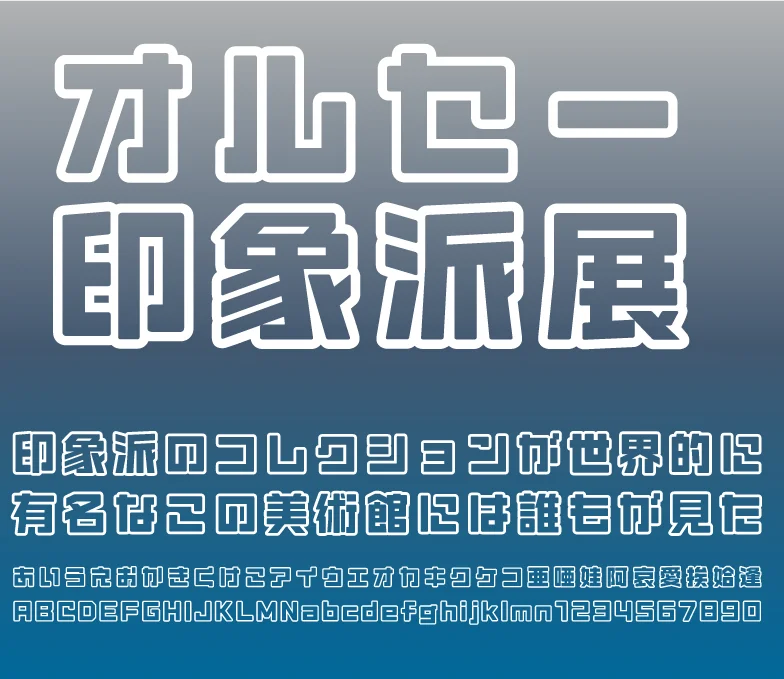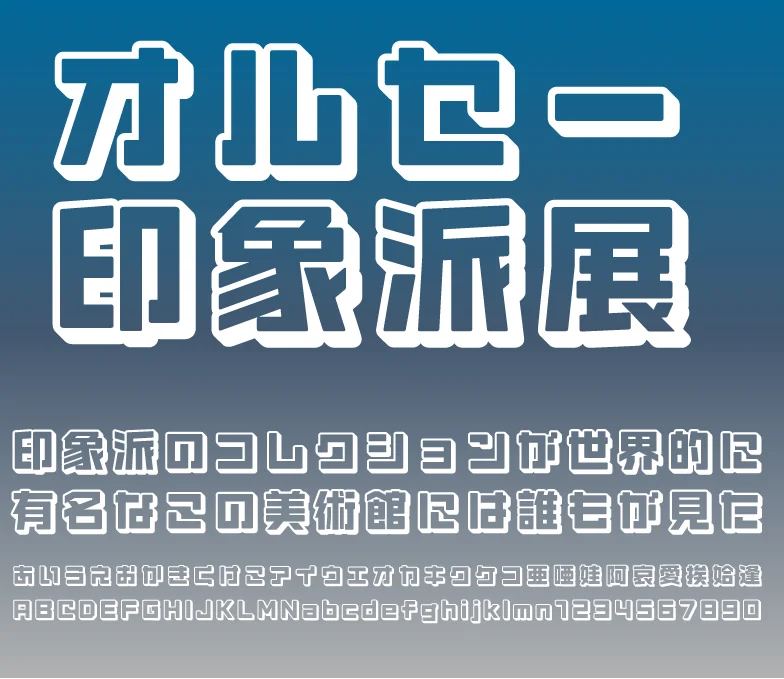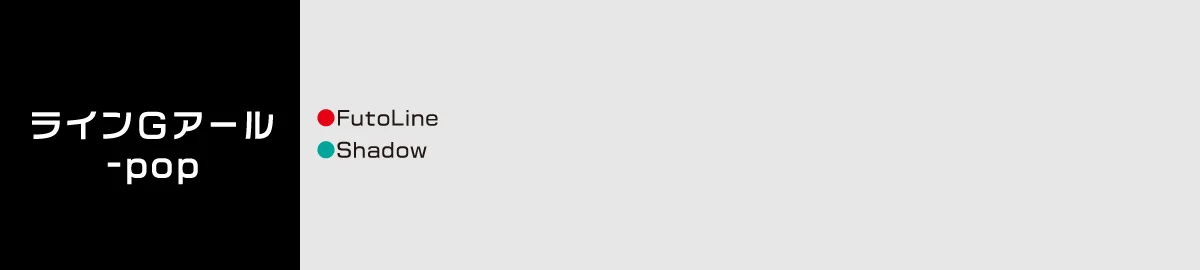
ラインGアール-popの特徴
「ラインGアール-pop」は、「ラインGアール」のデザインをベースに生まれた装飾書体です。文字の輪郭線のみを強調したデザインの「ラインGアール-pop-FutoLine」と、文字の背後に影を落とし立体的なデザインに見せる効果を持つ「ラインGアール-pop-Shadow」があります。
日本語フォントとしては数少ない装飾書体で、文字数も9,354文字と充実。実用性も十分です。(Adobe-japan 1-3準拠)
●FutoLine
ラインGアール-pop-FutoLine
●Shadow
ラインGアール-pop-Shadow